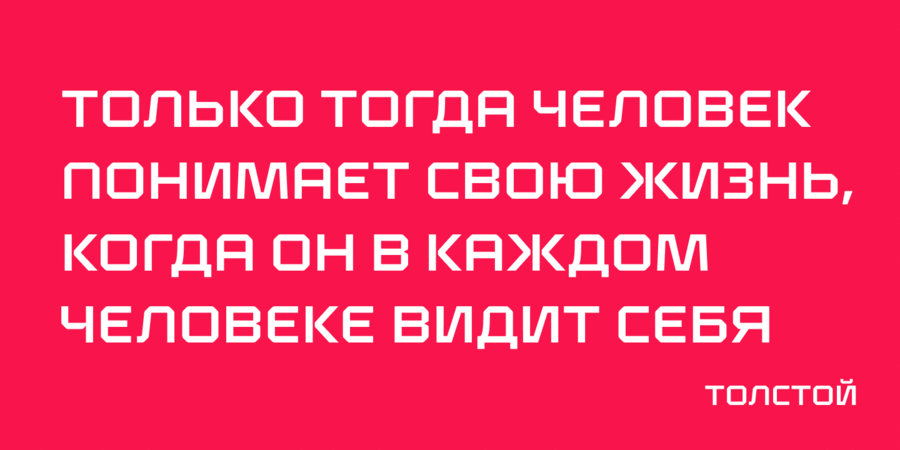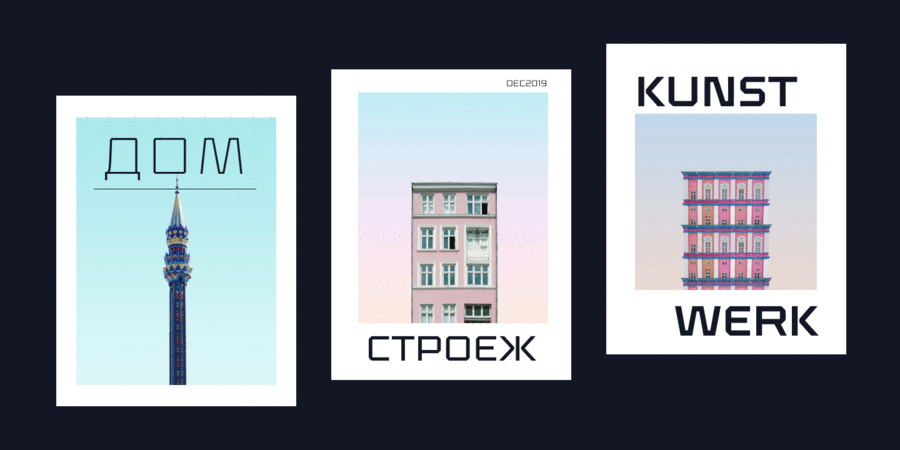
Стиль гарнітури:
Опис гарнітури Klapt Cyrillic – це розширена версія геометричного ґротеску Klapt. Сімейство з чотирьох накреслень включає розширений набір символів, підтримує більшість латинських мов, кирилицю і навіть в'єтнамську! Цей шрифт може бути і жирним і дуже тонким, призначений для різного дизайну, від брендингу й фірмового стилю до багатосторінкових видань для друку та екранів. Він відмінно підходить для акціденціі, особливо для заголовків, постерів, журналів, обкладинок, логотипів. Не соромтеся ділитися своїми дизайнами з використанням Klapt Cyrillic чи просто зв'яжіться з автором hi@seventype.com. Шрифт розробила Віторія Невес у 2019 році.
Особливості сімейства шрифтів Klapt CyrillicХіт десятиліття:
Асоціації з сімейством шрифтів Klapt CyrillicОсобистість і характер гарнітури:
рівний, квадратний, точний, логічний, холодний, автоматичний, техногенний, твердий, статичний, різкий, чіткий, стійкий, стабільний, тонкий, легкий, прямокутний, міський, сучасний, машинний, гострий, інженерний, урбаністичний, креслярський, скляний, крихкий, футуристичний, дротяний, Простий, надійний, впевнений, сталевий, космічний, байдужий, гранчастий, рубаний, переконливий, серйозний, сильний, індустріальний, залізний, мужній, військовий, армійський, промисловий, залізничний, ігровий, спортивний, робочий, кінематографічний
конструктор, креслення, архітектура, інженер, автоматика, урбаністика, наука, дизайн, Місто, статистика, гаджет, електроніка, технології, фантастика, космос, інструмент, робот, гра, прилад, айтішник, IT, айті, андроїд, залізо, коворкінг, рентген, астрономія, авто, промисловість, війна, армія, зброя, завод, металургія, верстат, тара, склад, порт, ящик, патрони, техніка, ремонт, депо, шолом, уніформа, вагон, авіація, літак, автомат, шутер, екшен, транспорт, страйкбол, взуття, залізниця, кубики, лего, комп'ютерна гра, спорт, машинобудування, охорона, захист, паливо, поліція, будівництво, цегла, автобус, робочий, кіно, кіберспорт Гарнітура асоціюється з віком: